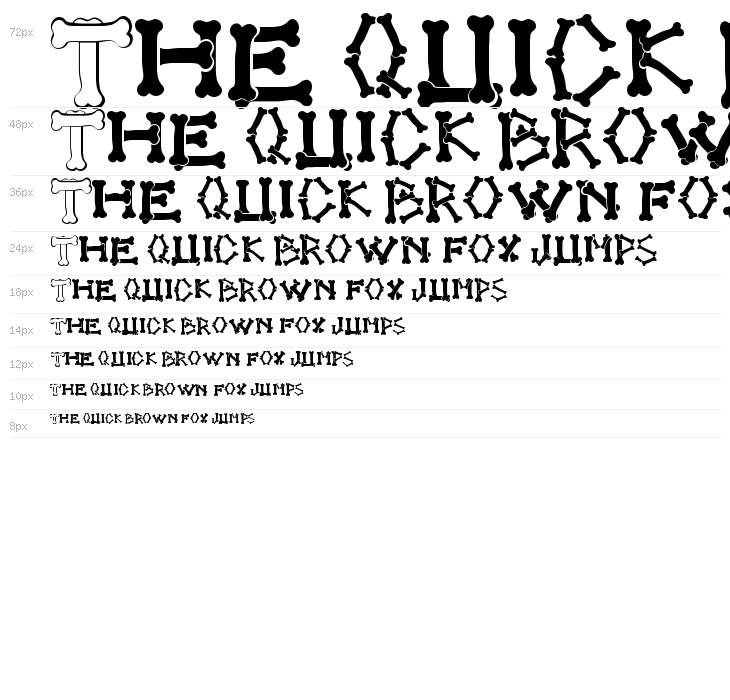
4 DOGS Font
| Caso de uso | Headlines, Logos, Themed Events |
| Proyectos propuestos | Ideal for Halloween invitations, pirate-themed events, children's party decorations, or any project needing a playful and bold aesthetic. |